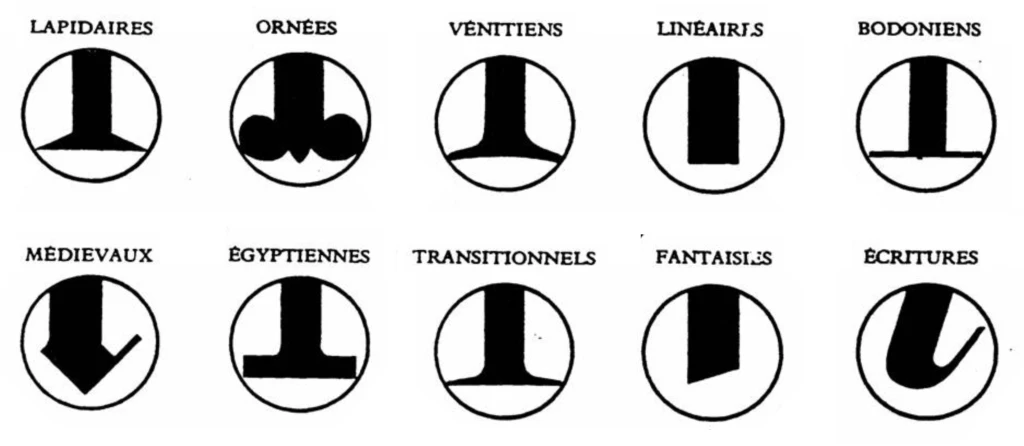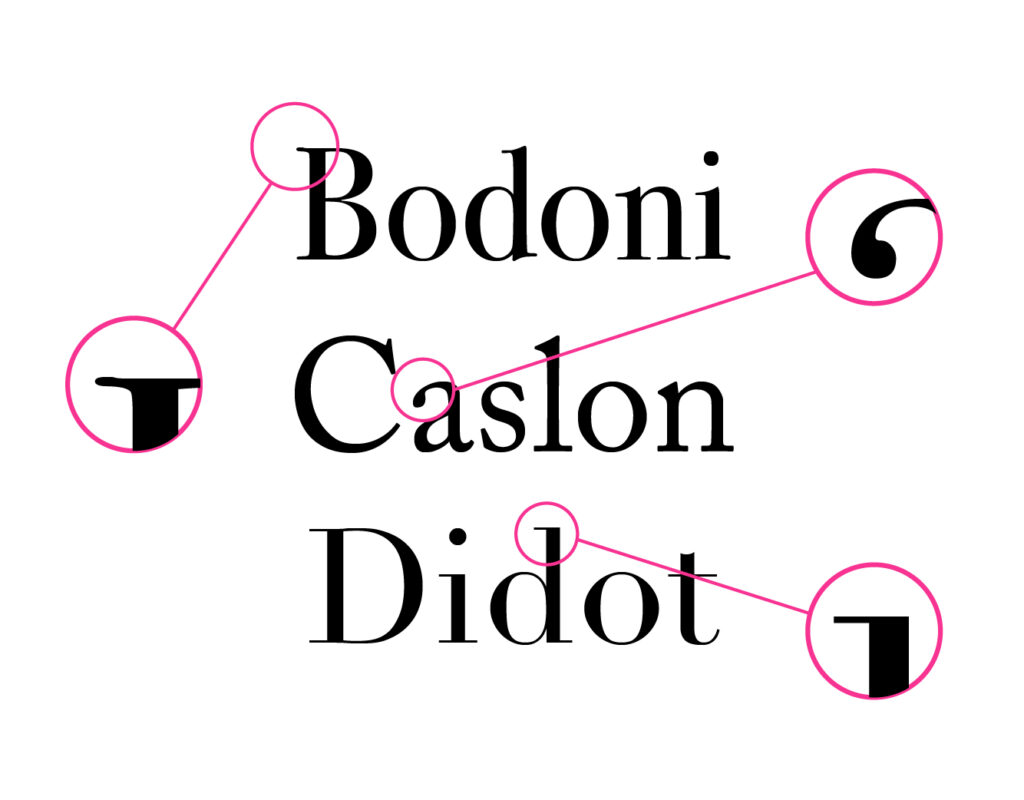
REMATE O SERIF
Es la terminación de los caracteres tipográficos.
Este término, también conocido como serif, serifa o gracia, es una criterio utilizado para la clasificación de familias tipográficas.
Imagen: clasificación tipográfica según Aldo Novarese
CLASIFICACION SEGUN NOVARESE